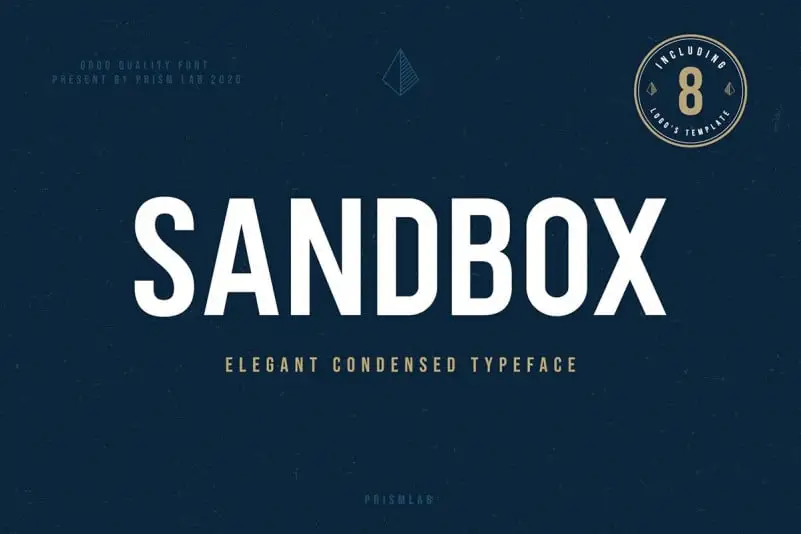
Sandbox Sans Serif Font – Fonte Grátis
Sandbox Sans Serif Font
Introduzimos a Sandbox Sans Serif Font, uma elegante fóntica sans serif que traz alternativas graciosas e ligaturas para facilitar sua criação de logotipos pessoais ou empresariais com um toque moderno. Esta fonte foi projetada e compartilhada pela PrismLAB. Inspirada em caracteres fortes e poderosos, a Sandbox apresenta um estilo sem serif compacto, destacando-se por sua aparência deslumbrante e textura lisa. Com seu modo de texto bravo e agudo, essa fonte é perfeita para estilos empresariais modernos e design gráfico contemporâneo. Experimente a Sandbox Sans Serif Font para dar um toque de originalidade ao seu próximo projeto visual.